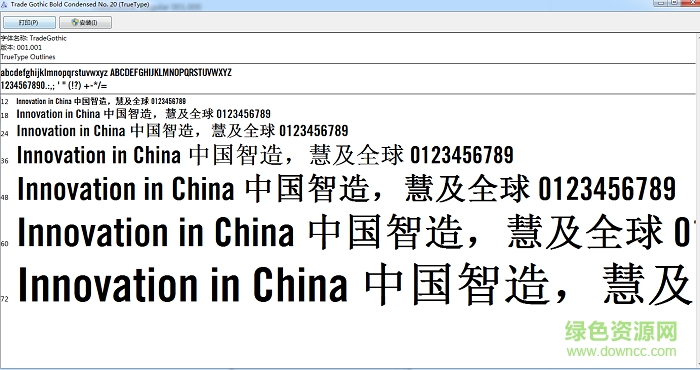
tradegothic boldcondtwenty
tradegothicboldcondtwenty字體是一款西方無(wú)襯線粗體字體,和中文黑體字體差不多,字面干凈比例精確,不過(guò)字體間距緊湊非常醒目,需要的朋友快來(lái)下載吧!
黑體字體介紹
在中文中,沒(méi)有襯線的字體通常稱為黑體,這時(shí)這個(gè)詞的范疇和無(wú)襯線字體(Sans-serif,亦稱無(wú)腳字)是類似的。所以在中文字體中常用“黑體”,在西文中常用“無(wú)襯線體”的稱呼。
tradegothic boldcondtwenty
無(wú)襯線字體介紹
襯線指的是字母結(jié)構(gòu)筆畫之外的裝飾性筆畫,沒(méi)有襯線的字體,則叫做無(wú)襯線體(sans-serif),它們往往擁有相同的曲率,無(wú)襯線體給人一種休閑輕松的感覺(jué)。